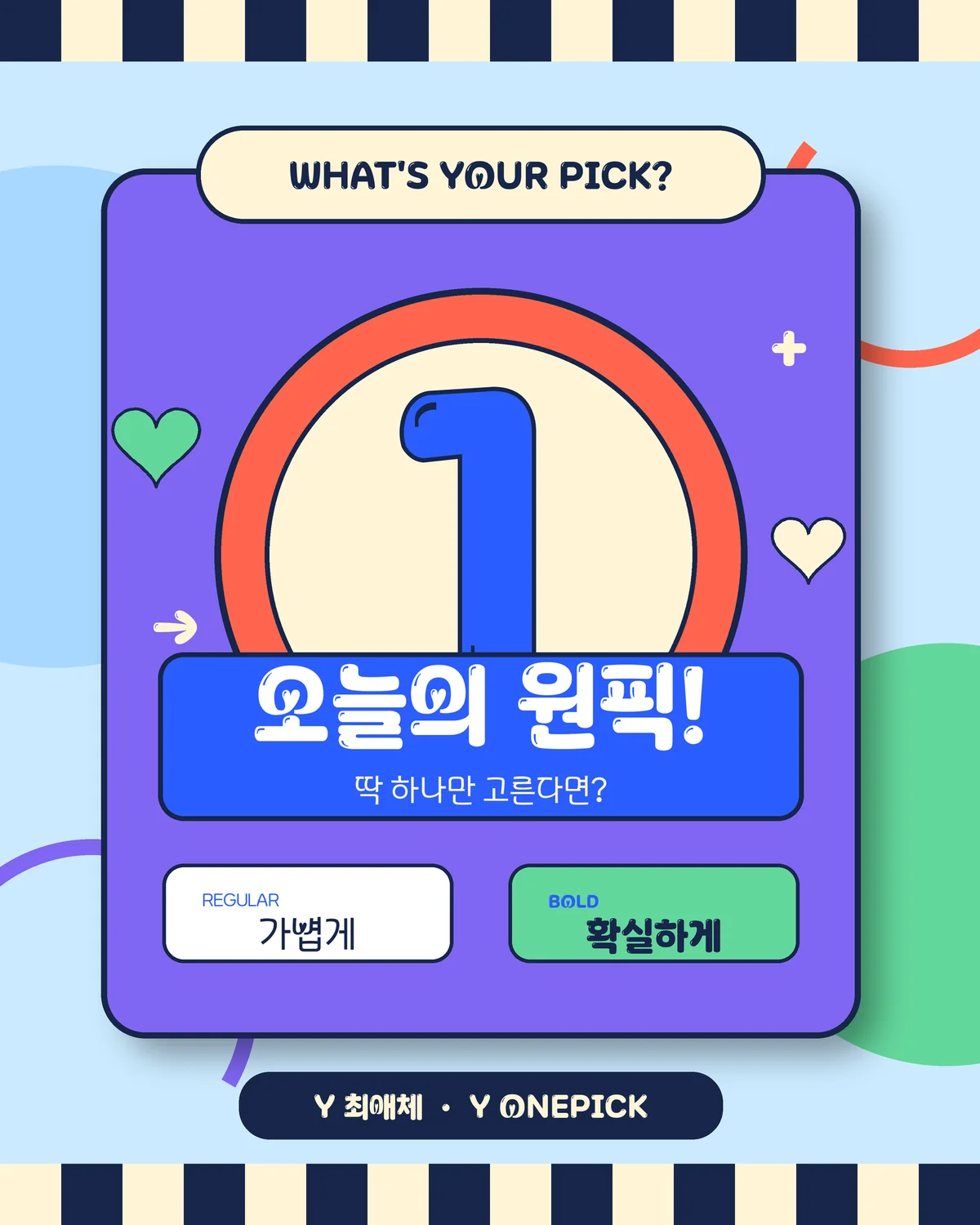
Y최애체 — (주)케이티에서 배포하는 무료 폰트입니다. 하트와 풍선을 모티브로 자유로운 곡선과 입체적인 조형을 담은 장식 서체
KT의 청년 브랜드 Y 서체 시리즈 여섯 번째로 2024년 한글날에 나왔습니다. 시리즈 가운데 팬덤 문화를 정면으로 다룬 서체입니다.
이름의 최애가 그 소재입니다. KT는 이 서체를 나만의 최애를 향한 Y의 반짝이는 애정을 자유로운 곡선과 하트 형태로 표현한 서체라고 설명합니다. 하트와 풍선을 모티브로 삼아 자유로운 곡선과 반사되는 느낌을 더했다고 덧붙입니다.
굵기는 Regular와 Bold 두 가지이고 Regular는 모바일 환경까지 지원합니다. 파일에서 재어 보면 받침이 붙을 때 글자 높이가 달라지는 탈네모틀이라 글줄에 리듬이 있습니다. 현대 한글 11,172자를 모두 담았습니다. 팬덤이나 응원, 굿즈, SNS 콘텐츠에 어울리고 격식 있는 문서에는 맞지 않습니다.